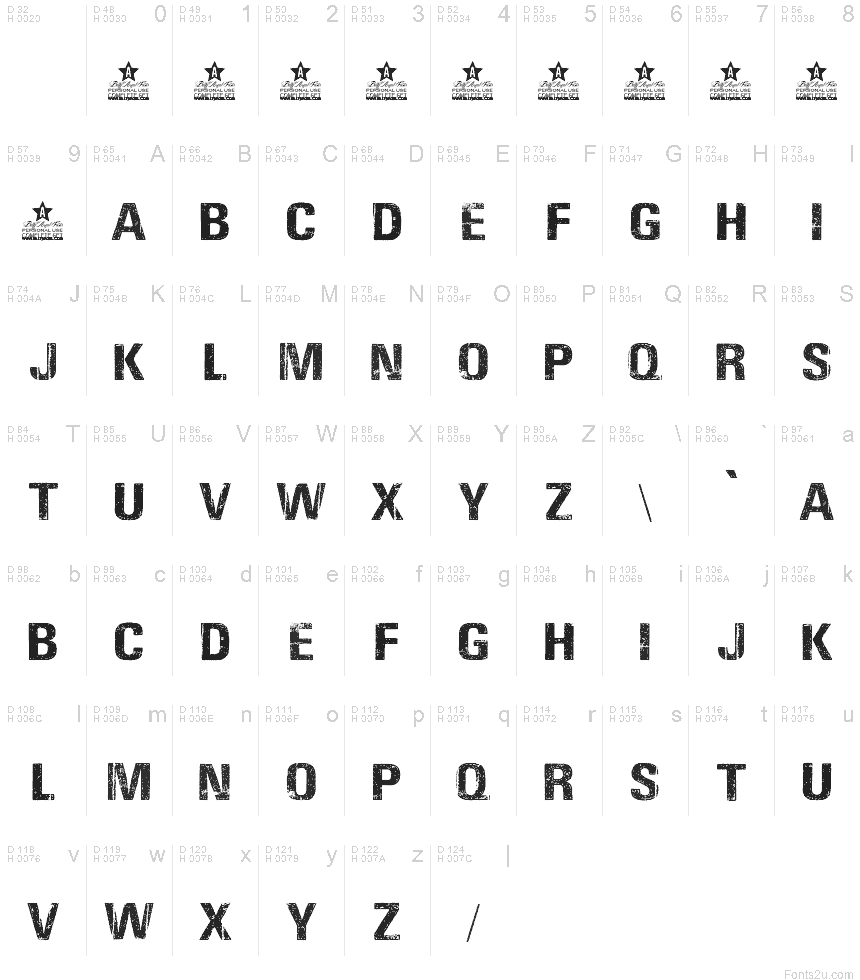
Creature
Creature autorstwa Billy'ego Argela to darmowy, erodowany krój typu display, który wprowadza surową, zniszczoną teksturę prosto do Twoich nagłówków. Pogrubione litery o prostych krawędziach wyglądają na podgryzione, z punktowymi uszkodzeniami – niczym farba odbita na chropowatym betonie lub zdrapana z wyblakłego plakatu. Efekt jest surowy, wyrazisty i namacalny – idealny, gdy chcesz, by Twoje napisy wyglądały, jakby przetrwały niejedną próbę czasu.
Dzięki Creature Twoje nagłówki natychmiast zyskują charakter horroru, thrillera lub miejskiego stylu grunge. Świetnie sprawdzi się na plakatach filmowych, ulotkach wydarzeń, okładkach albumów, tytułach gier, okładkach książek i grafikach na odzież. Ten darmowy font najlepiej prezentuje się w dużych rozmiarach, więc daj mu wybrzmieć w szerokich nagłówkach, a w tekście głównym połącz go z czystym krojem bezszeryfowym, aby zachować pełną czytelność.